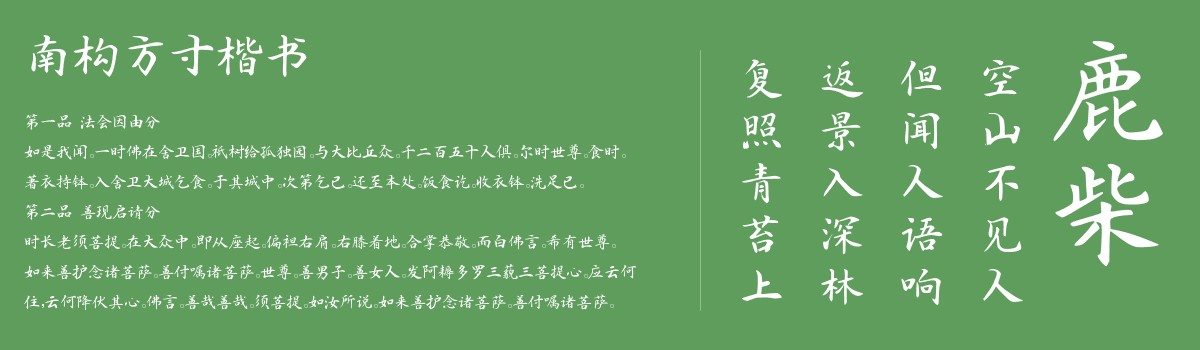
南构方寸楷书
南构方寸楷书是一款由字体家AI神笔造字生成的一款书法艺术字体,楷书风格,字型端正,一笔一划清晰有力。笔画端庄规整,横画平稳,收笔略带顿挫;竖画挺直,起笔有细微方折感。撇画舒展有度,捺画收笔沉稳;点画饱满,多呈斜势。结构中宫紧收,外笔画舒展,整体方正中见秀雅。笔画粗细变化自然,无刻意夸张,兼具楷书的严谨与细微灵动,呈现端庄稳重又不失清秀的视觉效果。比较适合用于艺术类装饰文字,海报、网页、广告设计,室内装饰,平面标题设计、食品包装、品牌标志等。